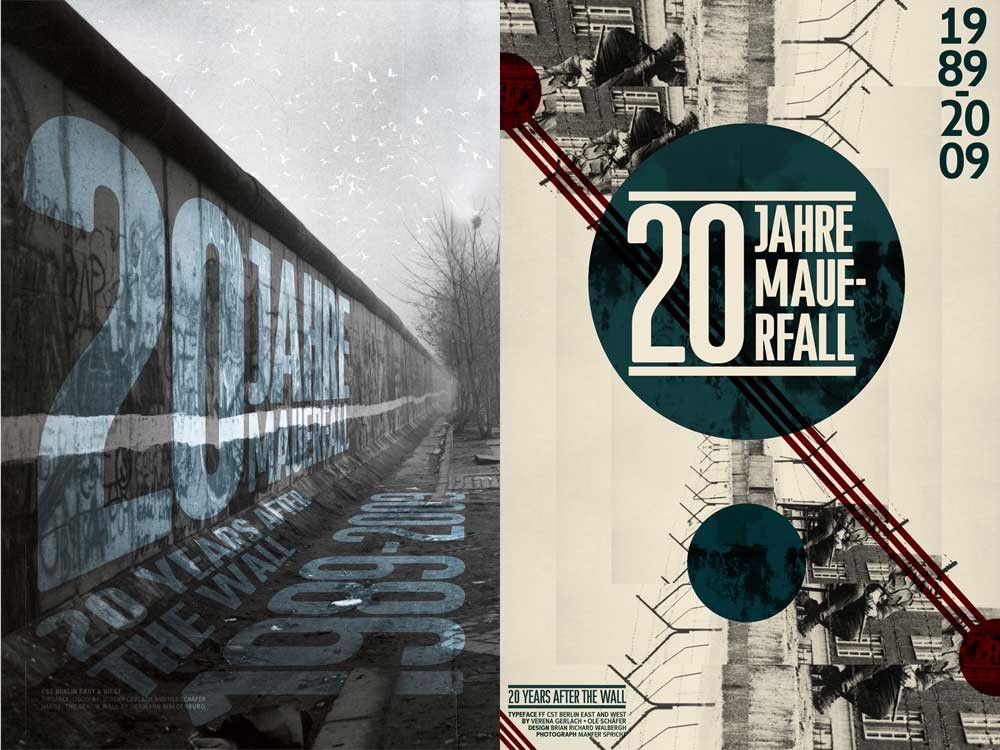
(Abbildung: »Typonauts in Space: 20 Jahre Mauerfall«, Poster vom type Workshop at MCAD)
In Berlin prägten über Jahrzehnte zwei unterschiedliche Straßenschild-Systeme das Erscheinungsbild von West und Ost. Die West-Variante geht auf Groteskschriften des Berlins der 30er Jahre zurück, im Osten bediente man sich einer 50er-Jahre-Grotesk mit technischer Ausprägung. Ole Schäfer und Verena Gerlach haben die Schrifttypen Ende der 1990er Jahre anhand der Originalschilder recherchiert, also nicht auf Vorlagen zur Schilderherstellung zurückgegriffen, und digitalisiert. So entstanden aus den im Straßenbild verwendeten Ausprägungen für den Ostteil zwei, für den Westteil eine Originalschrift: FF City Street Type East und FF City Street Type West.
Um die Schriften alltagstauglich zu machen, haben Gerlach und Schäfer die in Straßenschildern nicht vorkommenden Zeichen neu entworfen und stilistisch angepaßt. Zusätzlich haben sie zu den Schrifttypen je eine Headlineschrift entworfen, die mit den Strichstärken Regular, Medium und Bold für typografisches Arbeiten jenseits der Beschilderung bestens geeignet sind.
Wer mit der ziemlich weit verbreiteten DIN-Schrift unzufrieden ist bzw. an Grenzen stößt, den werden die 9 Schriftschnitte der FF City Street Type glücklich machen, die sogar Tabellenziffern Pfeile und andere nützlichen Zeichen enthalten.
Der Typo-Workshop scheint voll kreativ gewesen zu sein, sogar die Trennregeln werden zugunsten des Aussehens kreativ gehandhabt.
Wer die Regeln kennt …
Würde ich mal als künstlerische Freiheit auslegen.
Die pure Notlösung als künstlerische Freiheit auszulegen ist natürlich auch sehr kreativ. Aber bei Plakaten drückt man schon mal beide Augen zu. Wäre das ein Verpackungsdesign, hätte man dem Gestalter das Ding um die Ohren gehauen. :-)
Die Amistudies kannten unsere Trennregeln nicht, da sie alle nicht mit der deutschen Sprache vertraut waren, und ich war schon froh, dass ich Ihnen das »ß« erklären konnte. Also drücken wir hier mal ein Auge zu, ja?
Da beschäftigen sich Studenten in Minneapolis mit der jüngeren deutschen Geschichte – und Du kommst mit Trennregeln.
Na gut, den Amis sei es verziehen. ;-)
Die Mauer hat sich auch nicht an Trennregeln gehalten.
𝔒𝔯𝔡𝔫𝔲𝔫𝔤 muſs ſein!